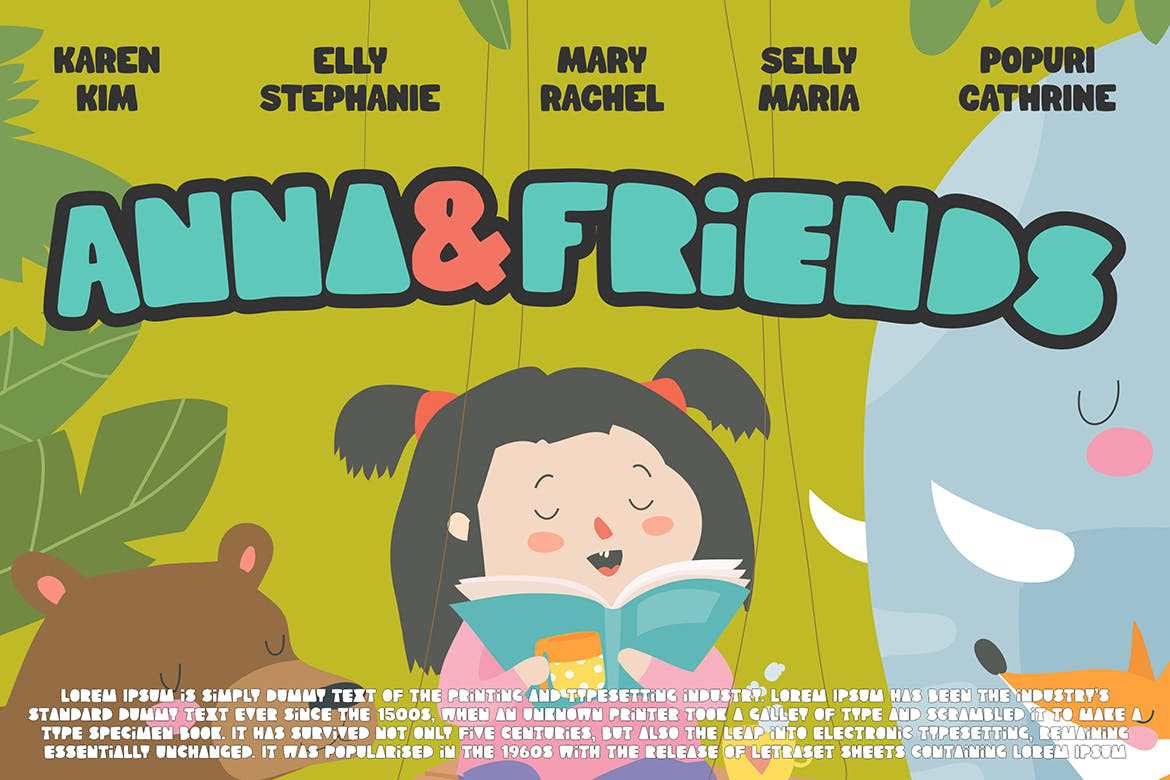
拥有BlockyShapeThatrotofJoyinit,将使您在屏幕上的每个角落都能突出儿童梦想。适合细分市场、在线游戏、海报、电影、快餐菜单、杂志、YouTube封面、YouTube缩略图、社交媒体封面,很快……拥有BlockyShapeThatrotofJoyinit,将使您在屏幕上的每个人都能突出儿童梦想。适合各种细分市场、在线游戏、海报、电影、快餐菜单、杂志、YouTubecover、youtubethumbnails、社交媒体封面,很快…